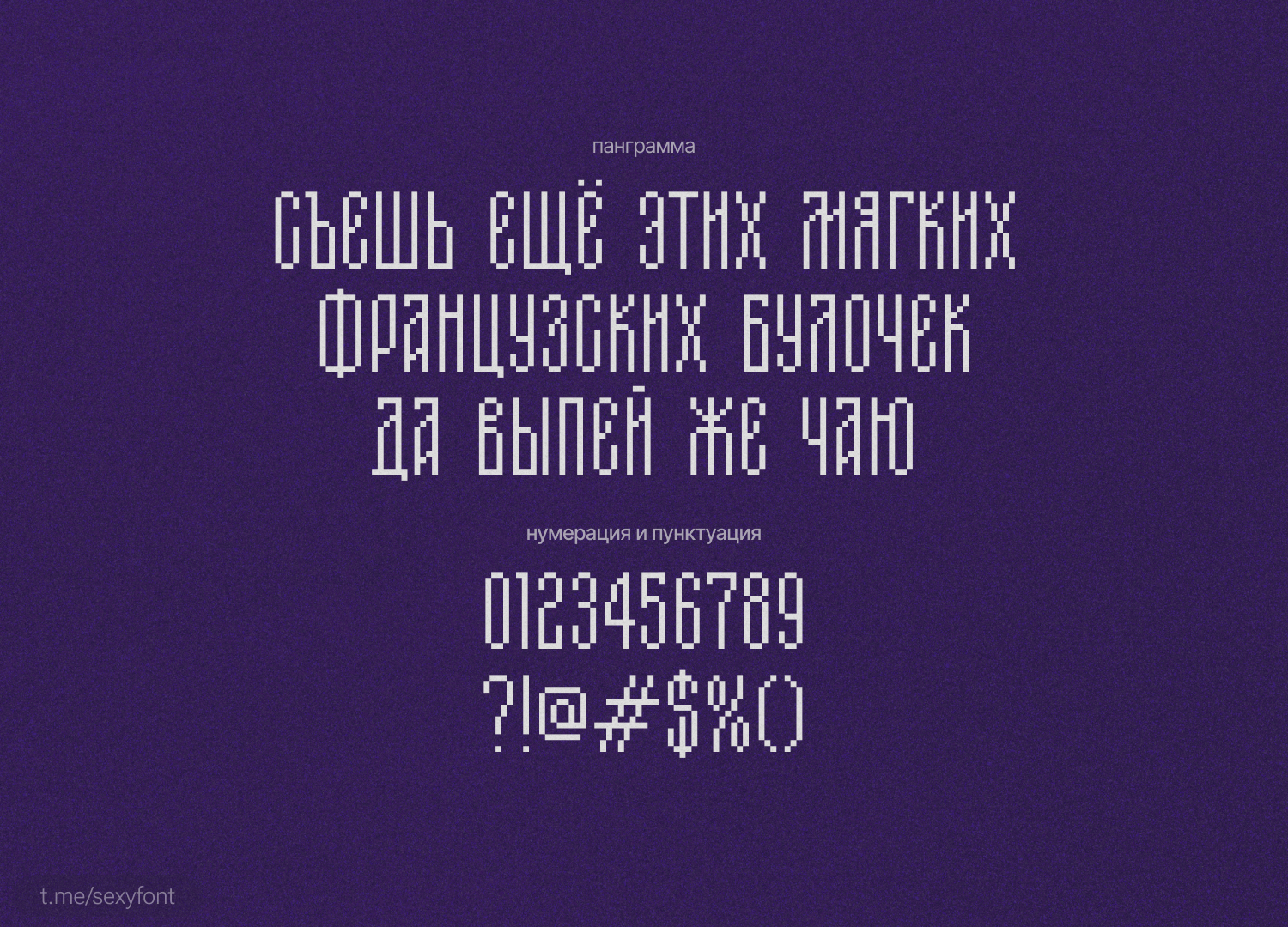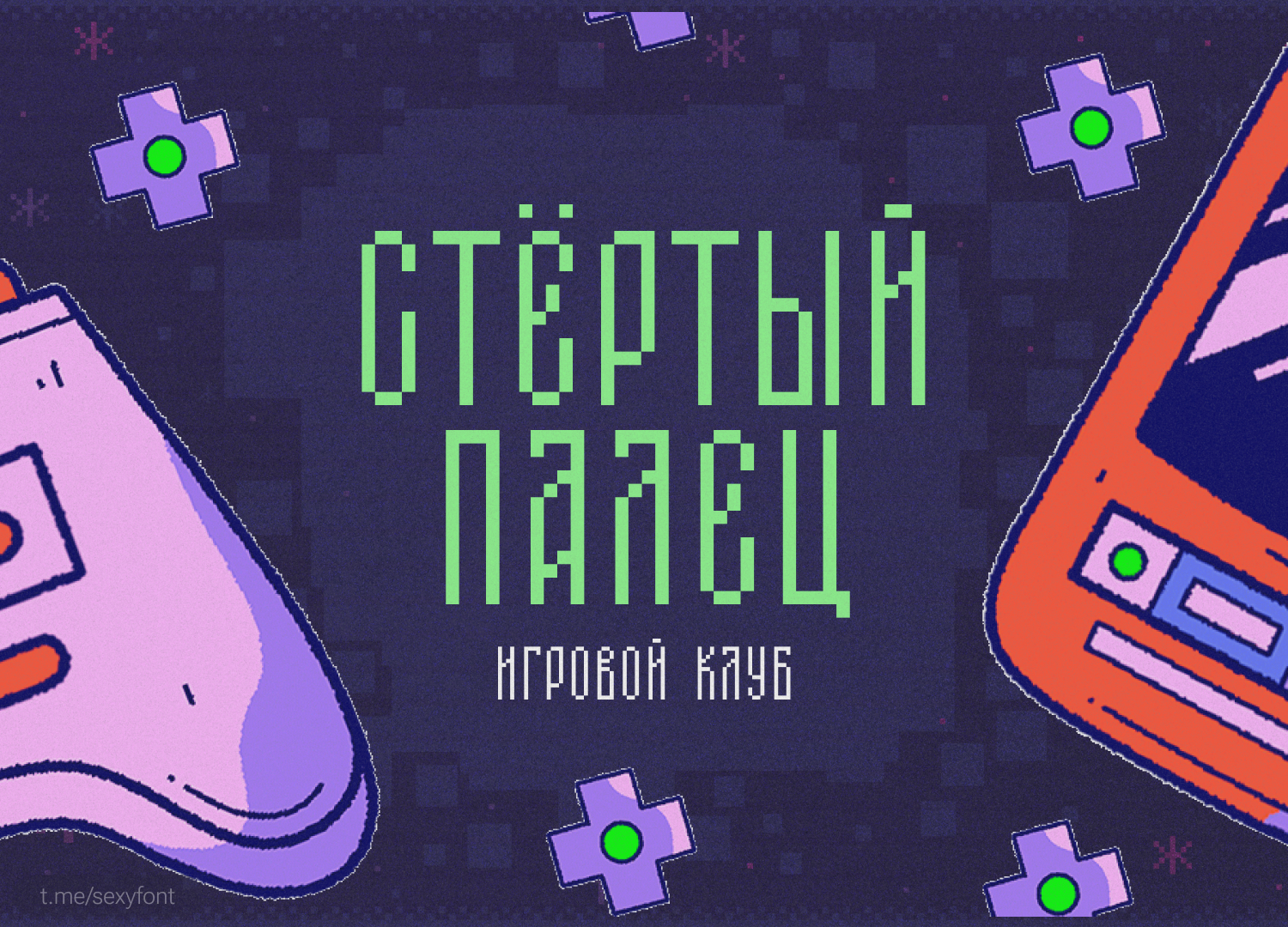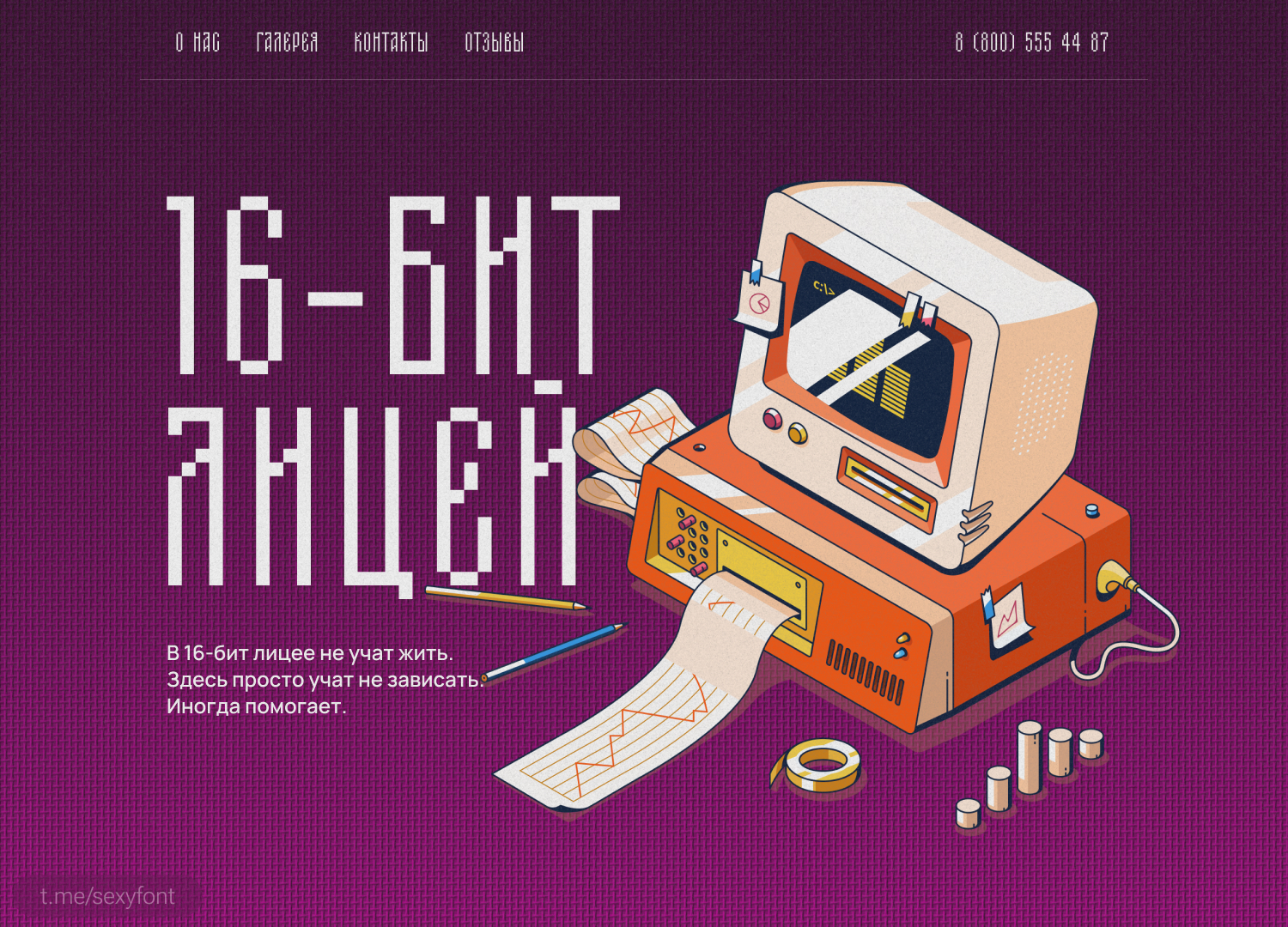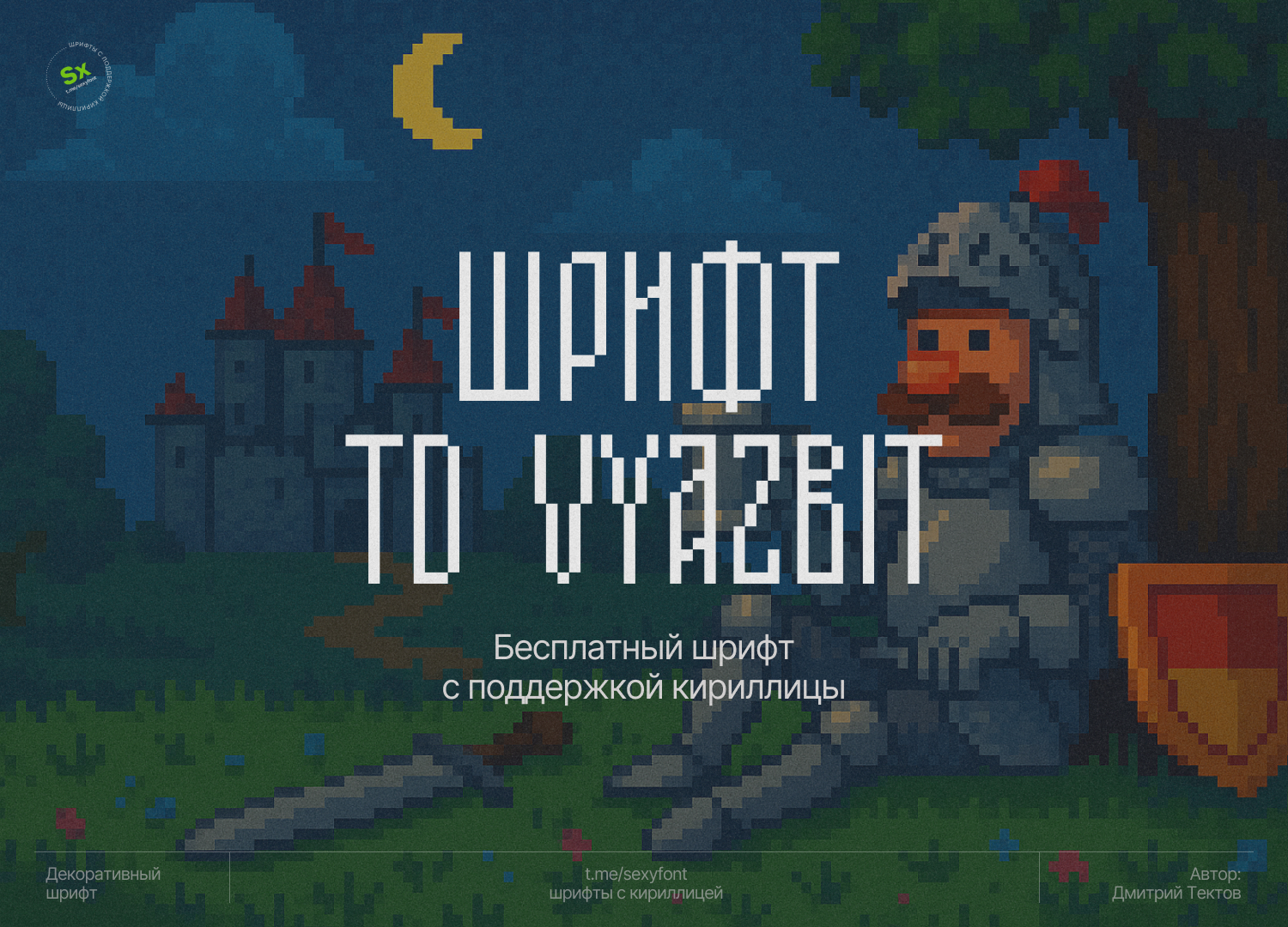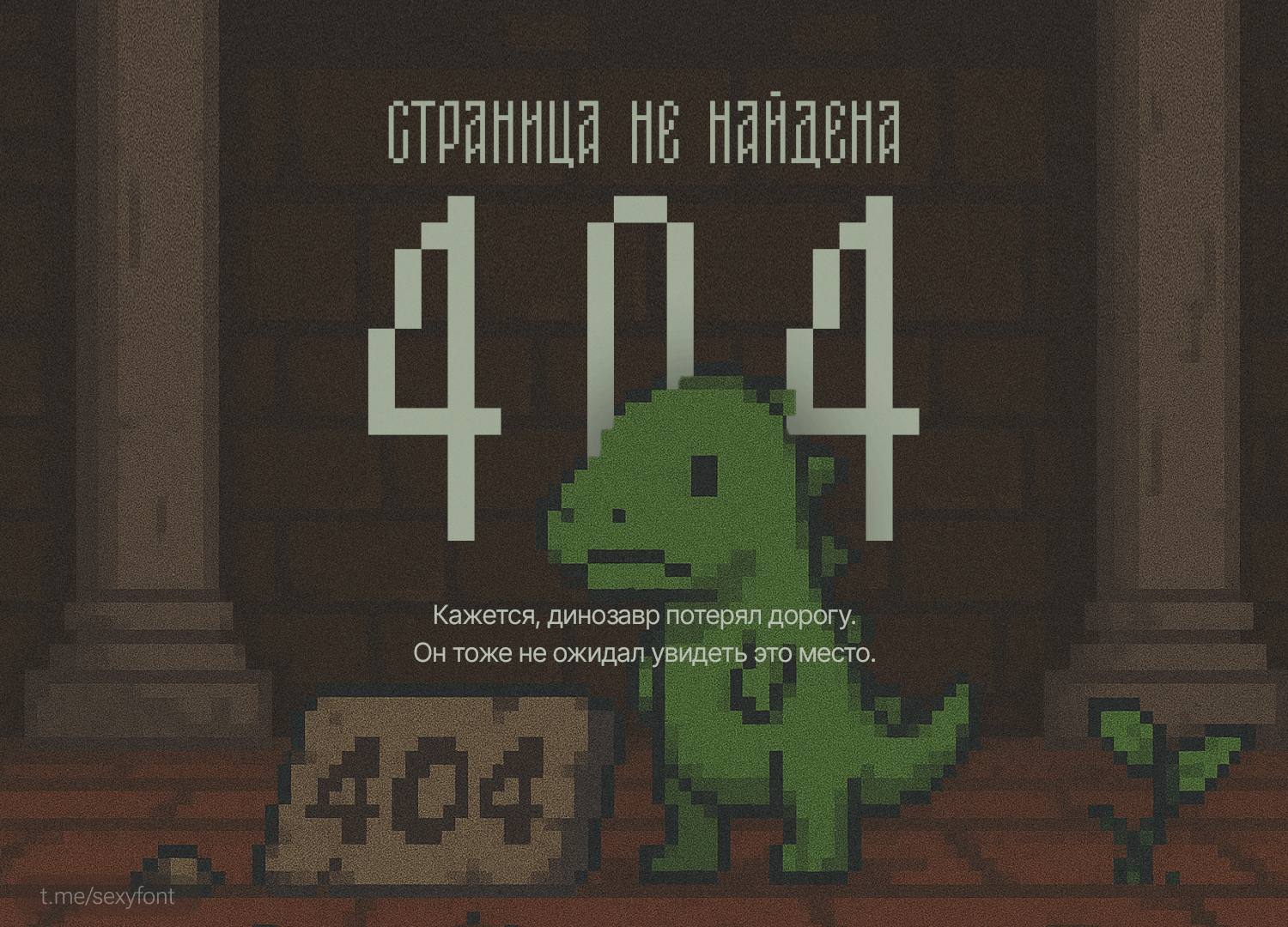
Шрифт TD Vyazbit
Новая презентация и шрифт. TD Vyazbit. Пиксельный шрифт для коротких заголовков) В идеале 1-2 слова. Иначе читаемость пропадает полностью.